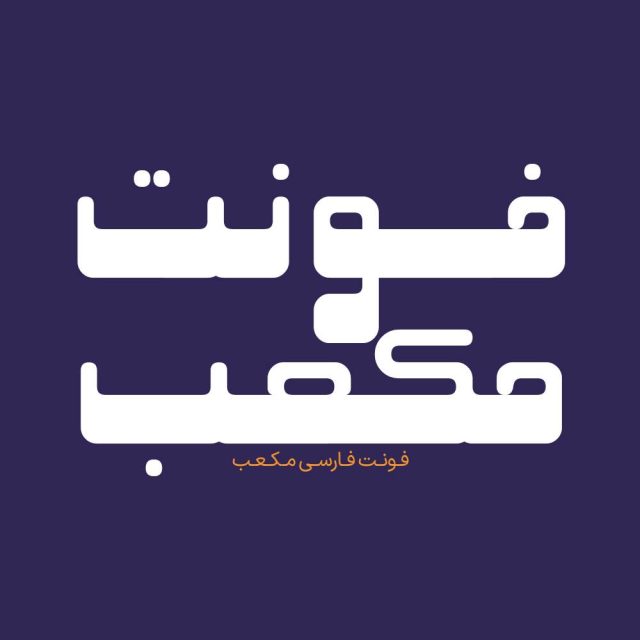
فونت فارسی مکعب Mokaab Font
فونت فارسی مکعب را میتوان در دسته فونت های نمایشی و هندسی قرار داد. بولد، استایل گرد و منحنی بودن گوشهها به جذاب شدن و حرفه ای شدن فونت مکعب بسیار کمک کرده است.
فونت مکعب بیشتر مناسب موضوعات تجاری و مدرن مثل صنایع بسته بندی (موادغذایی ومواد شوینده) است و برای عنوان فروشگاه، نشریات و کتاب های کودک، برندهای تجاری، طراحی لوگو و… کاربرد دارد. همچنین از این فونت در طراحی تابلوهای چلنیوم هم به دلیل ساختار منحصر به فردش می توانید استفاده کنید. در ادامه برای شما نمونه تایپ های این محصول حرفه ای رو آماده کردیم که میتونید مشاهده کنید.
پیشنمایش و نمونه تایپ های فونت مکعب